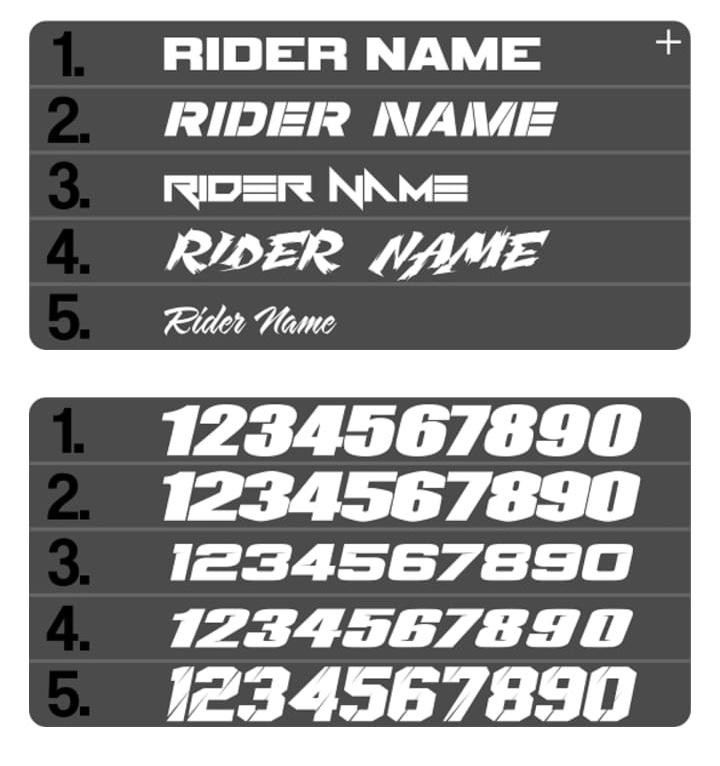
Suche Schrift aus Motorcross-Website (KTM Dekore)
Hallo suche für meine Cross die Schriftarten für meinen Namen und meine Startnummer:
bei den Zahlen suche ich die Nummer 5
bei den Buchstaben suche ich die Nummer 3
Das Bild mit den Beispielen habe ich von einer Website.
Kann man die Zahlenreihe auch raussuchen?
bzw die anderen Schriften auch noch bestimmen?
1. hat Ähnlichkeit mit der hier
2. https://www.dafont.com/search.php?q=Coulson&text=RIDERNAME
3. diese wirkt wie aus der hier konstruiert
4. https://www.dafont.com/search.php?text=RIDERNAME&q=Martyric+
5. https://www.myfonts.com/fonts/charlesborges/sarah-script/